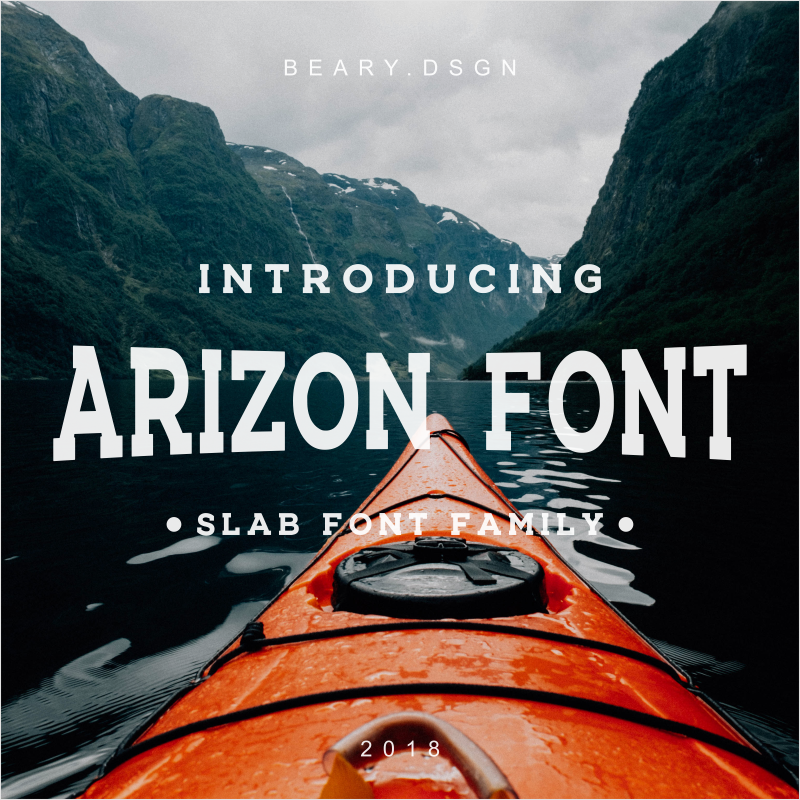
Arizon Slab Font Family – Download Grátis
A Arizon Slab Font Family é uma tipografia robusta e estilizada que se destaca no mercado das fontes serif. Ela é perfeitamente adaptada para diversas aplicações, desde criar logotipos impactantes até elaborar posters ambiciosos ou texturas em revistas de viagem. Suas linhas grossas e acentuadas são projetadas para maximizar a legibilidade, tornando-a uma escolha excelente para qualquer projeto que exija leitura fácil. Seja ela um design minimalista para o seu site ou uma impressão vibrante na sua camisa de aventura, a Arizon Slab sempre fará você se destacar. Esta fonte é perfeita tanto para as mais simples como para as mais elaboradas aplicações visuais, garantindo que seus projetos tenham um toque único e impactante.
Designer: bearydsgn